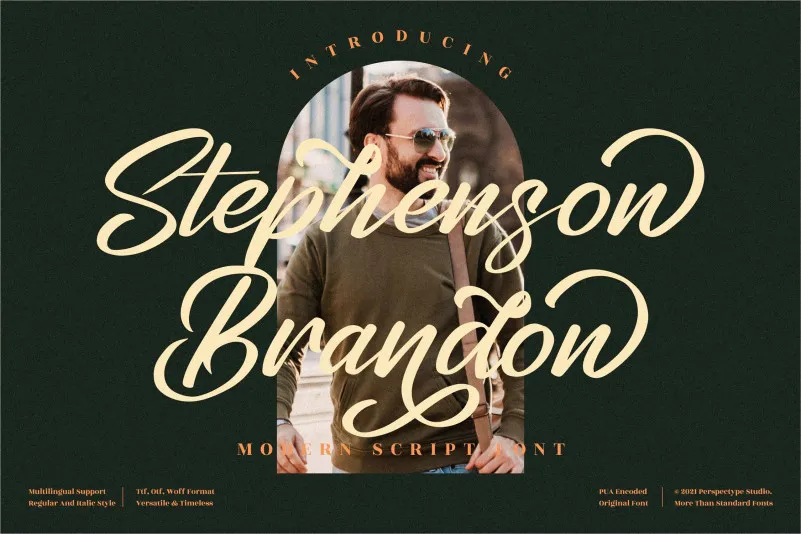
Stephenson Brandon Font – Download Grátis
Esta fonte ‘Stephenson Brandon’ é uma elegante caligrafia cursive com toques relaxados que traz a essência do papel à digital. Perfeita para um amplo espectro de usos, desde identidades visuais e cartões de visita até selos e faixas, ela oferece um estilo casual mas sofisticado capaz de dar vida aos seus projetos mais criativos. Seja para criar uma identidade visual memorável, embalagens que chamem a atenção ou até mesmo materiais promocionais como camisetas personalizadas, esta fonte é o ideal. Ela traz sua essência única e envolvente diretamente à sua tela, tornando-a uma escolha indispensável para designers e criativos em busca de um toque único e sofisticado.